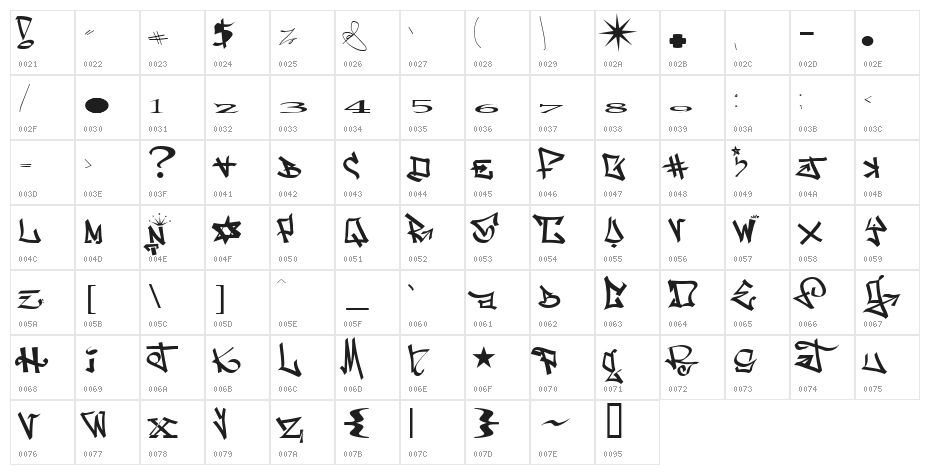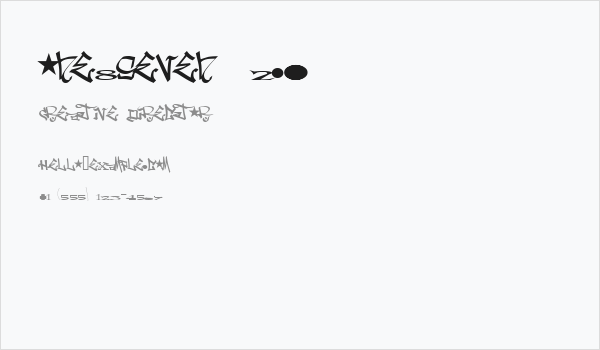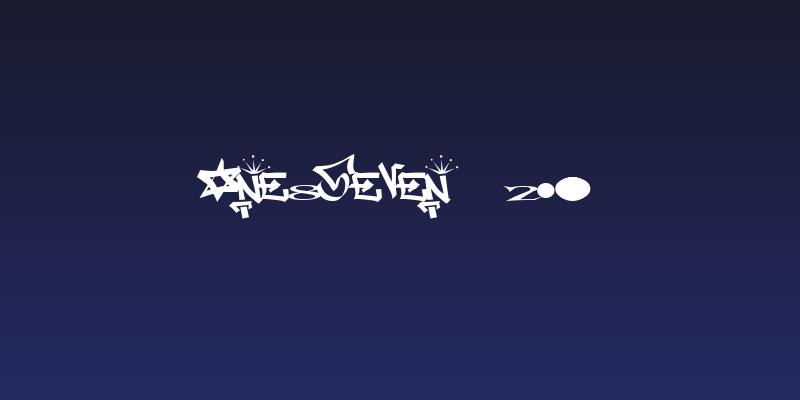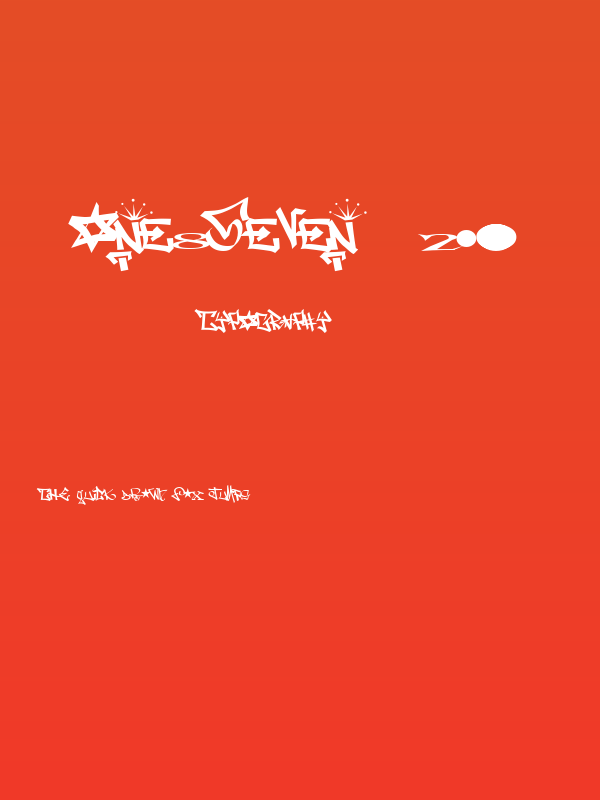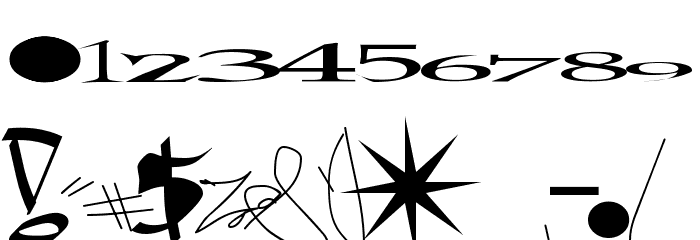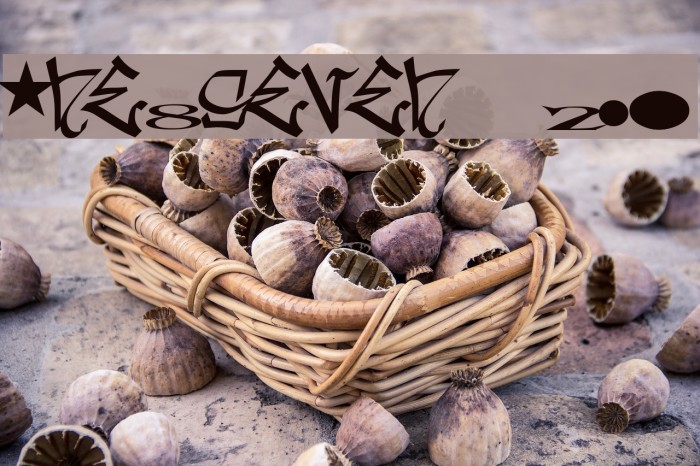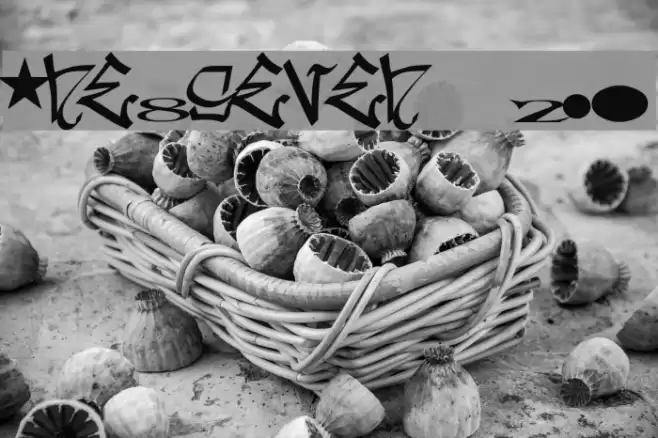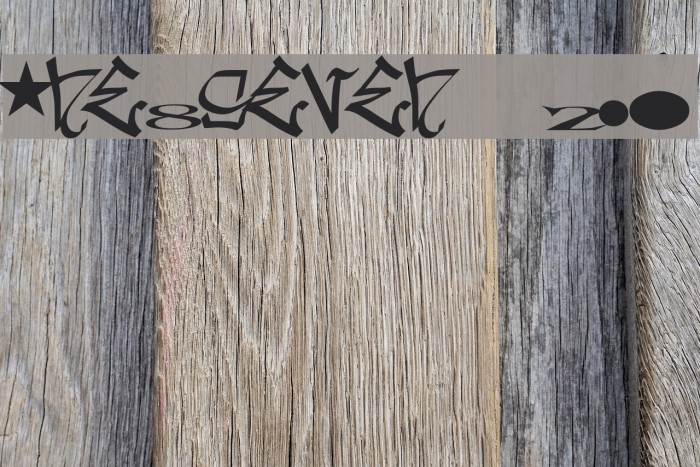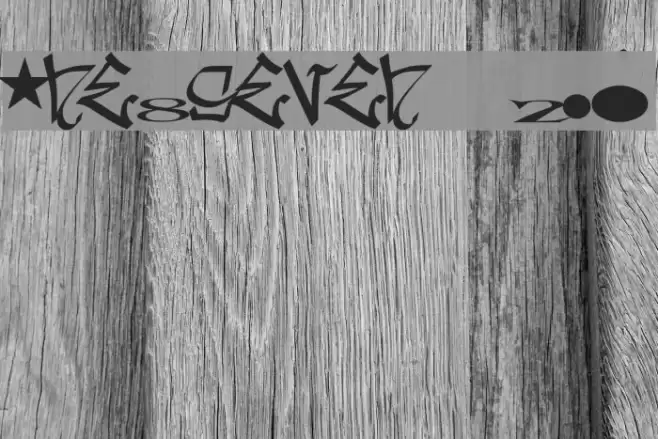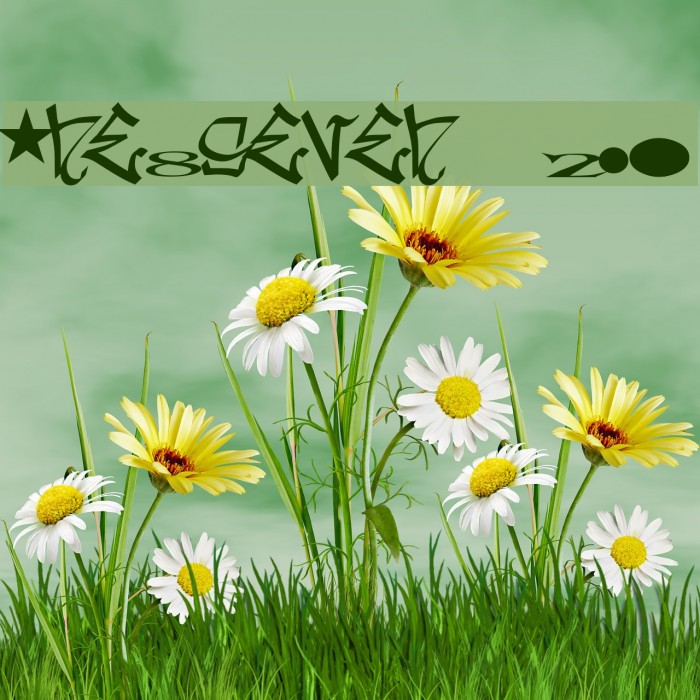
one8seven 2.0 Font
| Stil general | Modern, Urban, Edgy |
| Caz de utilizare | Logos, Posters, Album Covers |
| Proiecte propuse | Ideal for street art designs, hip-hop album covers, urban-themed posters, and edgy branding projects. |